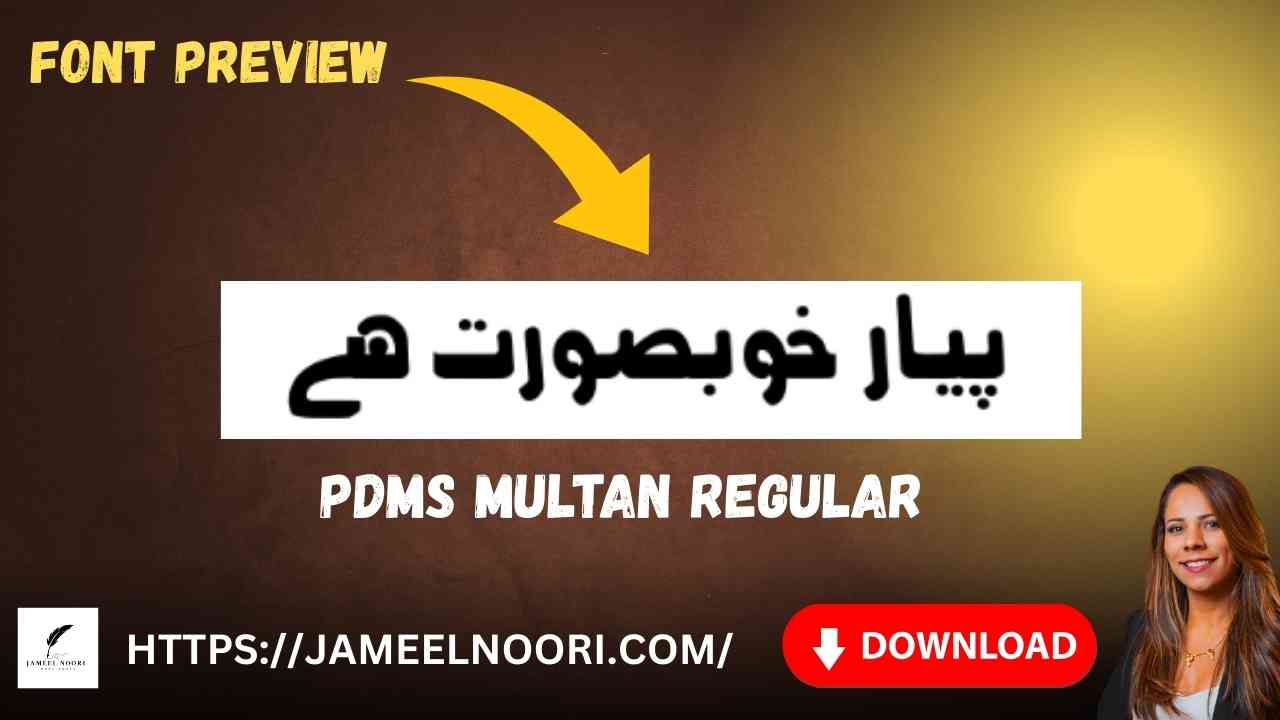
Introduction to Download Urdu font PDMS Multan Regular
Agar aap Urdu typing aur designing ke shaukeen hain to Download Urdu font PDMS Multan Regular aapke liye ek best choice hai. Ye ek Regular TrueType Font hai jo Urdu likhne walon ko professional aur stylish experience deta hai. Pakistan ke users specially Multan, Peshawar, Lahore aur Karachi mein is font ko zyada pasand karte hain kyunki iska style readable aur attractive hai.
Ye font InPage, MS Word, CorelDraw aur Adobe Photoshop jaise designing software ke sath easily compatible hai. Iska clear aur smooth design newspaper headlines, Urdu books, assignments, official documents aur social media posts ke liye best mana jata hai. PDMS Multan Regular ka lightweight structure aur Unicode support isse fast aur error-free banata hai. Agar aap Urdu fonts collection build kar rahe hain to ye font zaroor include karna chahiye.
Features of Download Urdu font PDMS Multan Regular
Features of PDMS Multan Regular:
- Easy readability aur clean design
- Official Urdu typing ke liye recommended
Why Choose Download Urdu font PDMS Multan Regular?
Aaj kal internet par hundreds Urdu fonts available hain, lekin Download Urdu font PDMS Multan Regular apni simplicity aur readability ki wajah se sabse alag hai. Ye font specially official documents, Urdu websites aur digital designing me use hota hai. Agar aap ek content creator, designer ya student hain to ye font aapke liye ek ultimate choice ho sakta hai.
Benefits of Using Download Urdu font PDMS Multan Regular
- Urdu typing aur designing ke liye perfect readability
- Pakistan ke top designers aur students ki expert choice
Conclusion – Download Urdu font PDMS Multan Regular
Agar aap ek stylish aur readable Urdu font dhoond rahe hain to Download Urdu font PDMS Multan Regular aapke liye best option hai. Is font ka use karke aap apne Urdu projects ko professional touch de sakte hain. Lahore, Karachi aur dusre shahron me is font ki demand bohot high hai. Is liye abhi download karke apne typing aur designing ka level upgrade karein.
Is PDMS Multan Regular good for web designing?
Yes, due to its readability and lightweight design, it is great for web designing.